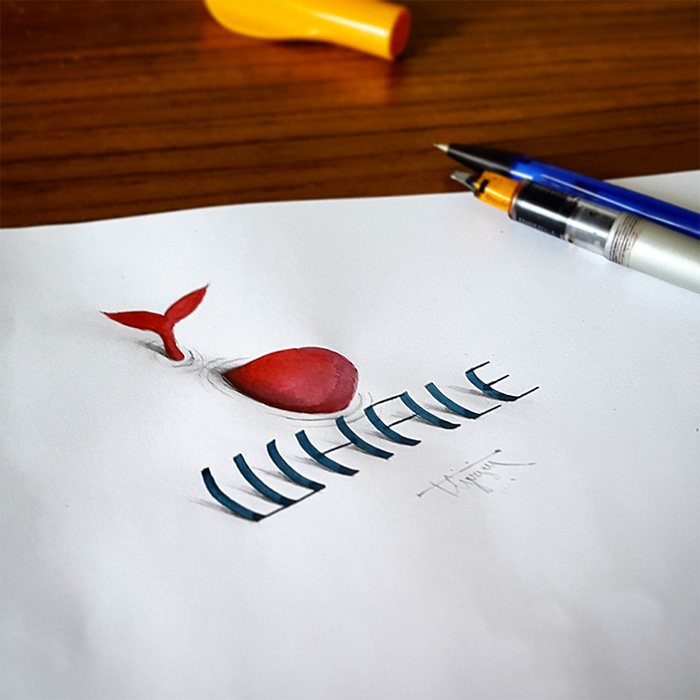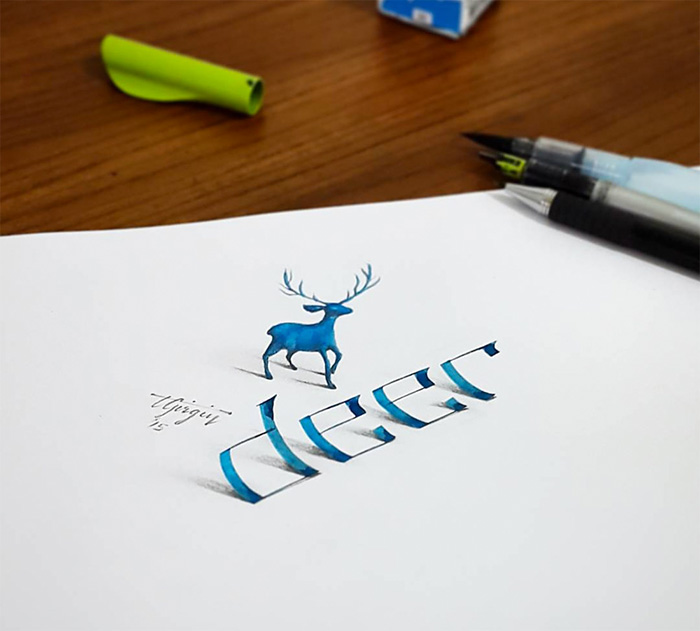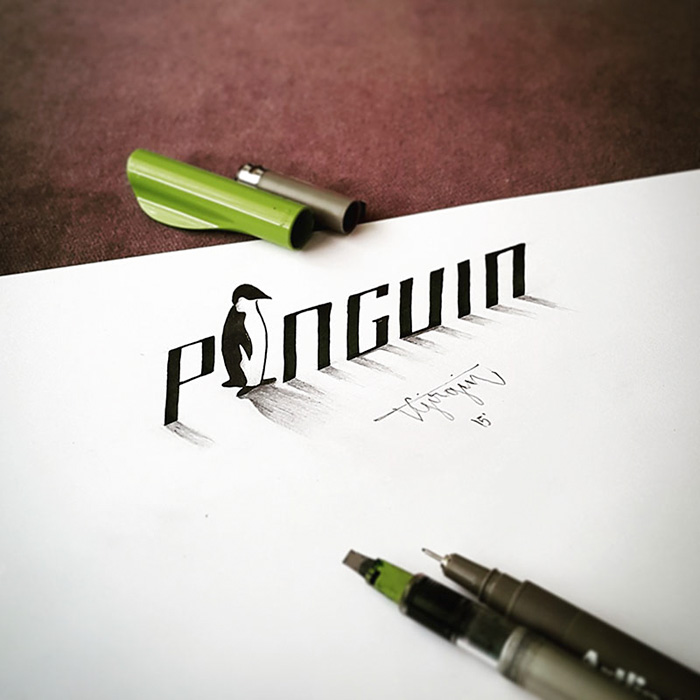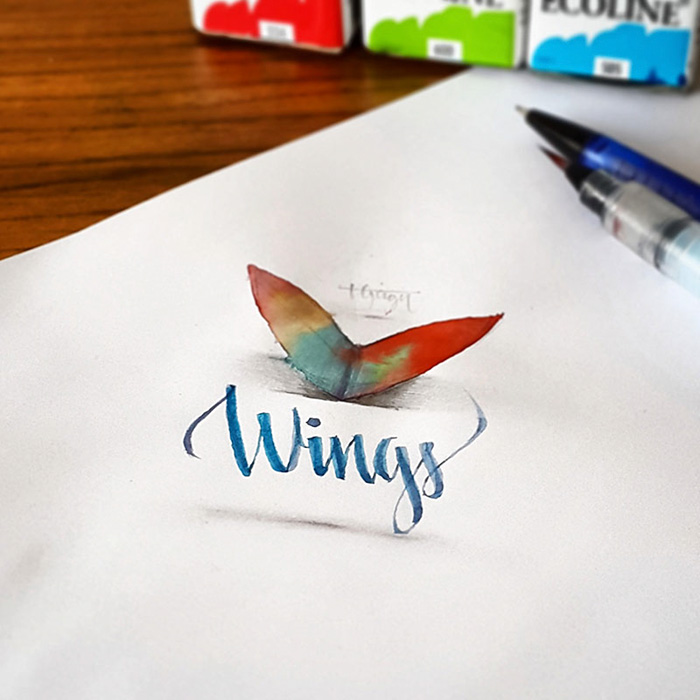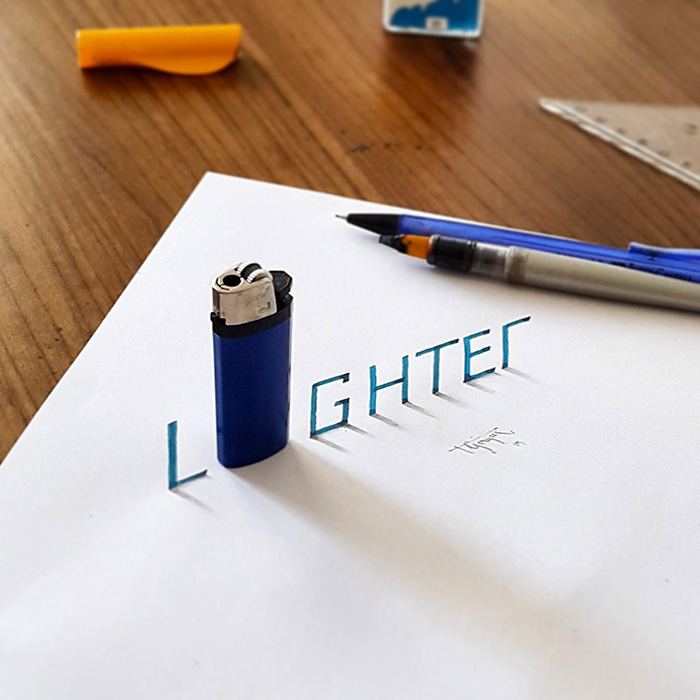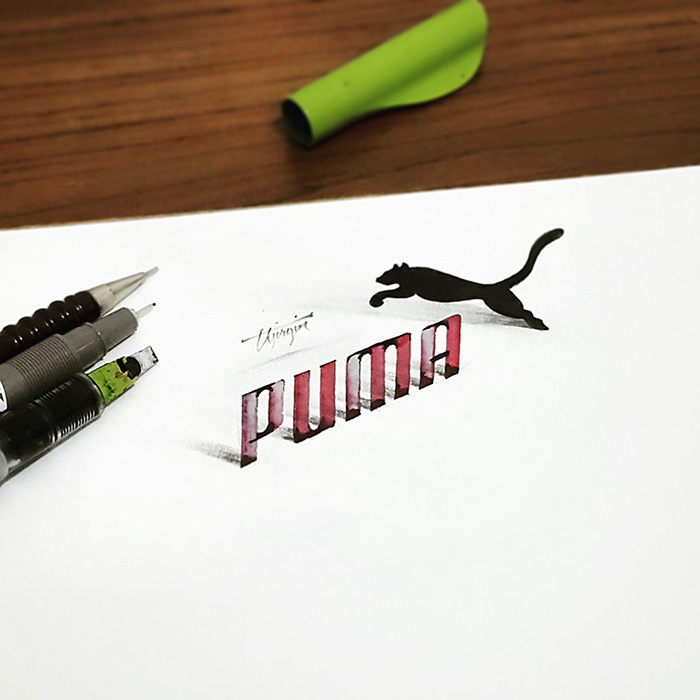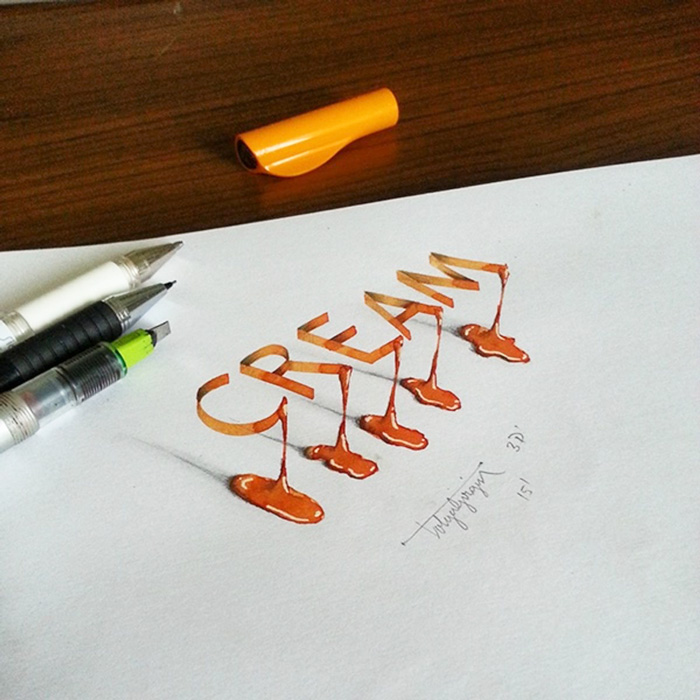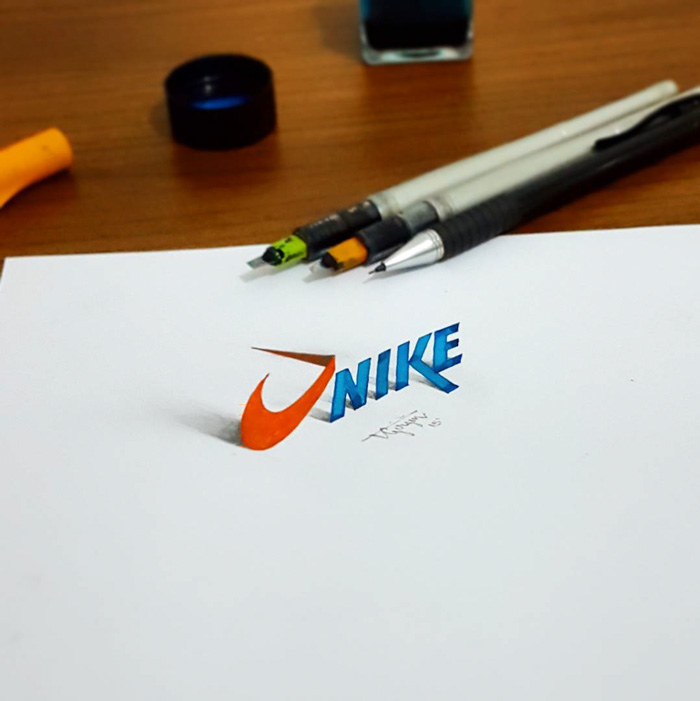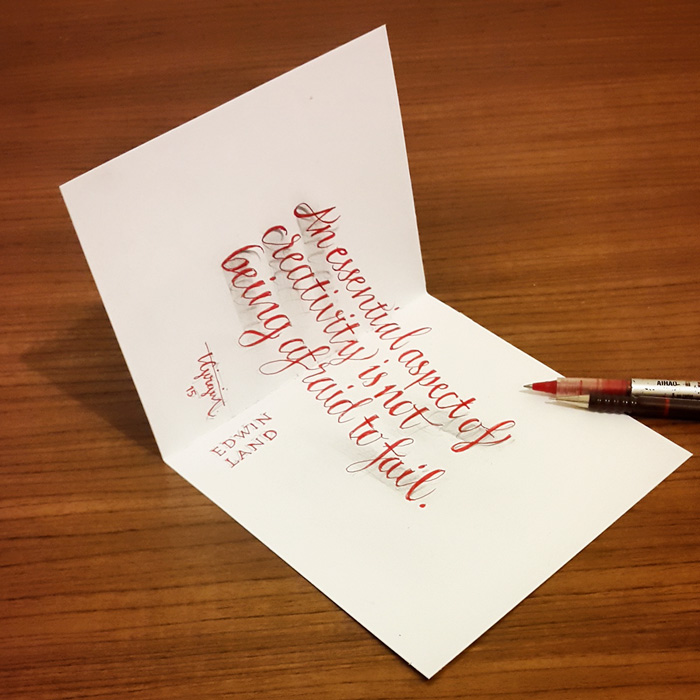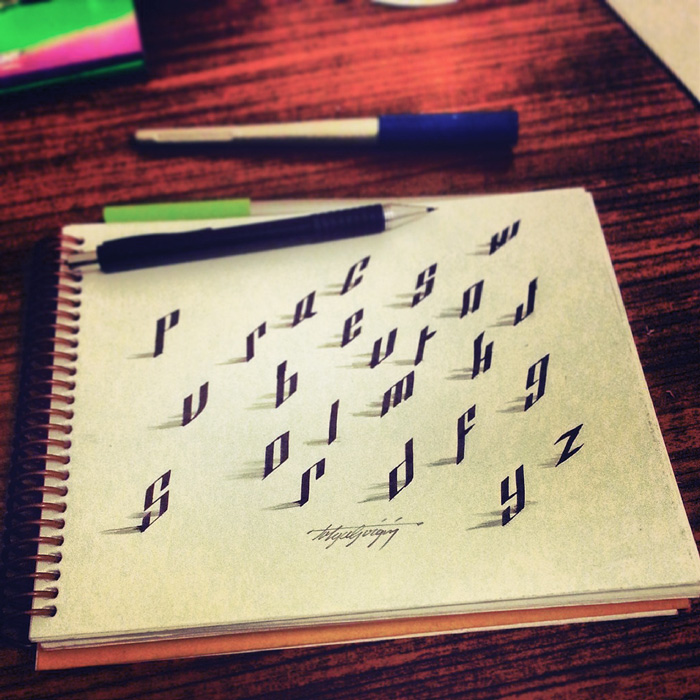
Tipografia / Lettering criativos feitos em 3D
Tolga Girgin é engenheiro elétrico e designer gráfico e atualmente vem compartilhando na internet seu talento como design e com suas tipografias feitas a mão e em 3D.
Ele diz que depois que começou a criar tipografias no papel, sua esposa o incentivou a compartilhar com outras pessoas e também a criar sem parar, ter cada vez mais inspiração para criar muitas opções.
Tolga diz que passa cerca de 20 minutos para criar tipografias curtas, como em palavras, mesmo utilizando 3D, mas que quando resolve criar textos maiores seu trabalho pode demorar até 3 horas para ficar pronto.
Em alguns casos, Tolga diz que sua experiência com cálculos o ajuda a criar de uma forma melhor e mais certeira.